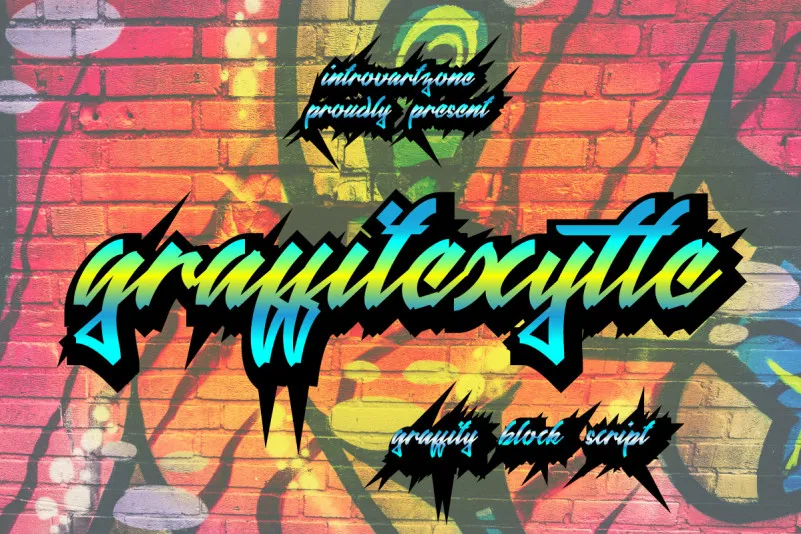
Graffitexytte Font – Download Grátis
Graffitexytte é uma fonte graffiti que traz uma riqueza artística à sua marca ou projeto gráfico. Inspirada nos escritos na rua, esta tipografia moderna e vibrante está perfeitamente adaptada para headlines de jogos móveis e aplicativos digitais. Seu estilo block script não só proporcionará um impacto imediato, mas também dará uma dose atraente ao seu design impresso, como camisetas, adesivos ou até mesmo panfletos. Suas linhas fortes e seus tons vivos oferecem um toque único e memorável aos seus projetos. Não importa o tipo de projeto, seja ele digital ou impresso, Graffitexytte tem a capacidade de torná-lo singular e imbatível. Ideal para quem busca manter uma identidade forte em sua comunicação visual. Experimente dar vida às suas criações com esta fonte inspirada no graffiti, ideal tanto para design gráfico como para mídia impressa e digital.